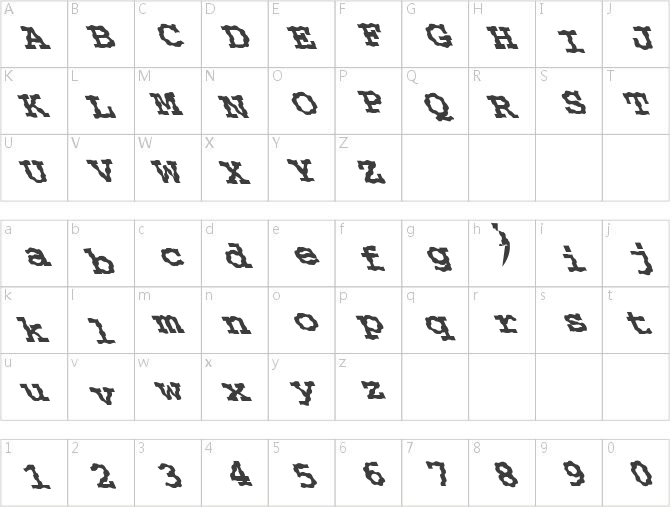
FZ BASIC 54 WAVEY LEFTY
FZ BASIC 54 WAVEY LEFTY介紹
FZ BASIC 54 WAVEY LEFTY字體字庫是一款讓人賞心悅目、百看不厭的英文字體,適合各類廣告和產品包裝設計應用,字體大小0.11MB,格式為ttf字體,上傳用戶是惠祥博達,作者/版權方為未知